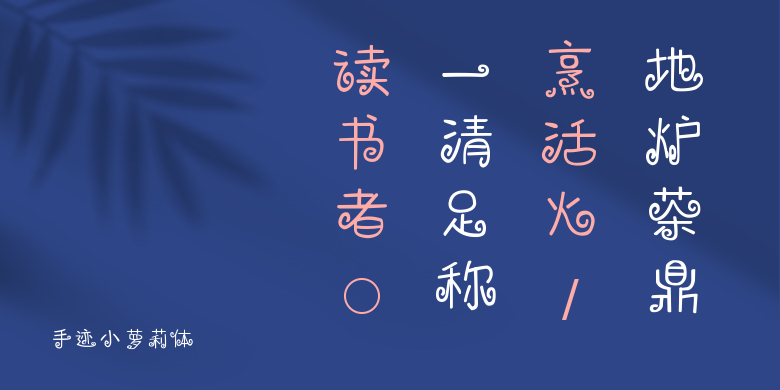
手迹小萝莉体
手迹小萝莉体,这款字体结构工整、笔画清晰,兼顾美观与易读性,适用于标题、正文、海报、包装、LOGO 等多种场景。字形优雅稳定,风格百搭耐看,适配日常排版与创意设计,让文字呈现更舒适、更具质感。手迹小萝莉体一笔一画,皆是细节,以均衡的比例、流畅的线条打造舒适视觉体验,字形端正大气,风格简约现代。无论是商业设计、品牌宣传还是日常排版,都能轻松驾驭,让文字更有格调与力量。手迹小萝莉体字体下载。